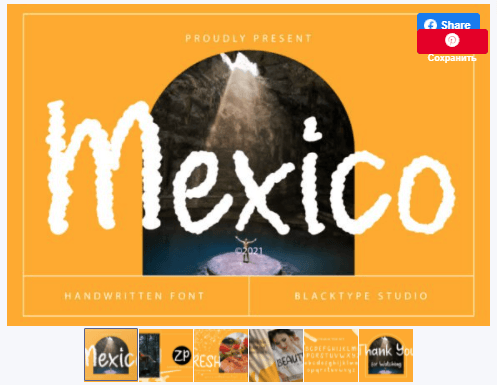
Mexico Font
Mexico - симпатичный экранный шрифт с кисточкой. Этот оригинальный вид подойдет для самых разных творческих идей, от фирменных бланков и заголовков до канцелярских принадлежностей.